Sudah lama sejak kami update terakhir font terbaru, maka dari itu kali ini kami mengumpulkan beberapa koleksi font terbaru dan terupdate di bulan januari 2016 ini yang bisa anda download secara gratis.
Arciform Free Font
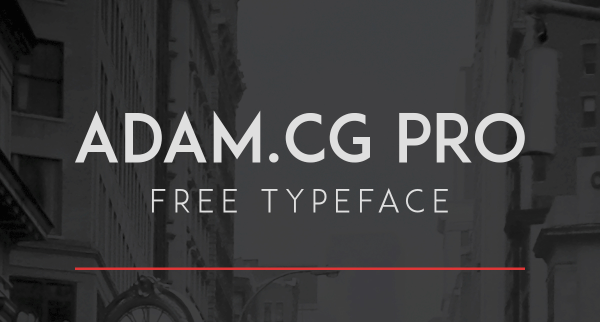
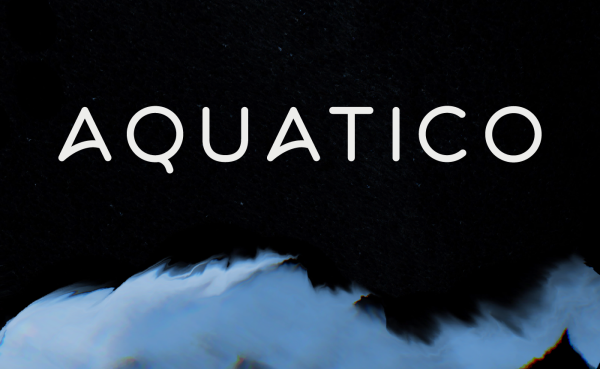
Argon adalah font yang unik didesain secara kreatif terlihat seperti sebuah labirin namun tetap mempertahankan bentuk yang mudah dibaca.
BEYNO Free Typeface